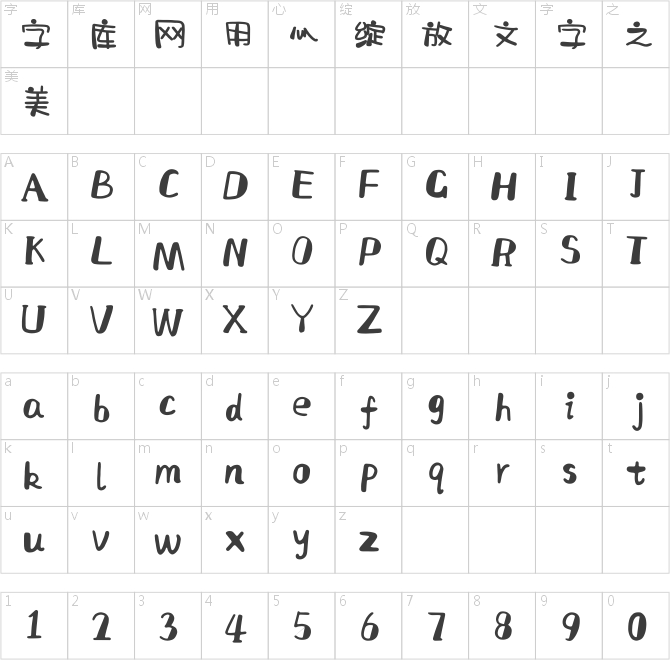
字心坊pop团圆体 详情页
字体名称: 字心坊pop团
字心坊pop团圆体
字心坊pop团圆体介绍
POP为point of purchase。即“购买点广告”,又可译成“店前广告”。最早主要应用于超市卖场及各类零售终端专卖店等,既能使整体版面更活泼,又可起到有效的视觉表达,刺激引导消费。此款字体是偏圆润、可爱的风格,保留了pop字体的特性,同时兼具了识别性。用于平面海报、网页、影视、包装等都有极佳的视觉效果。